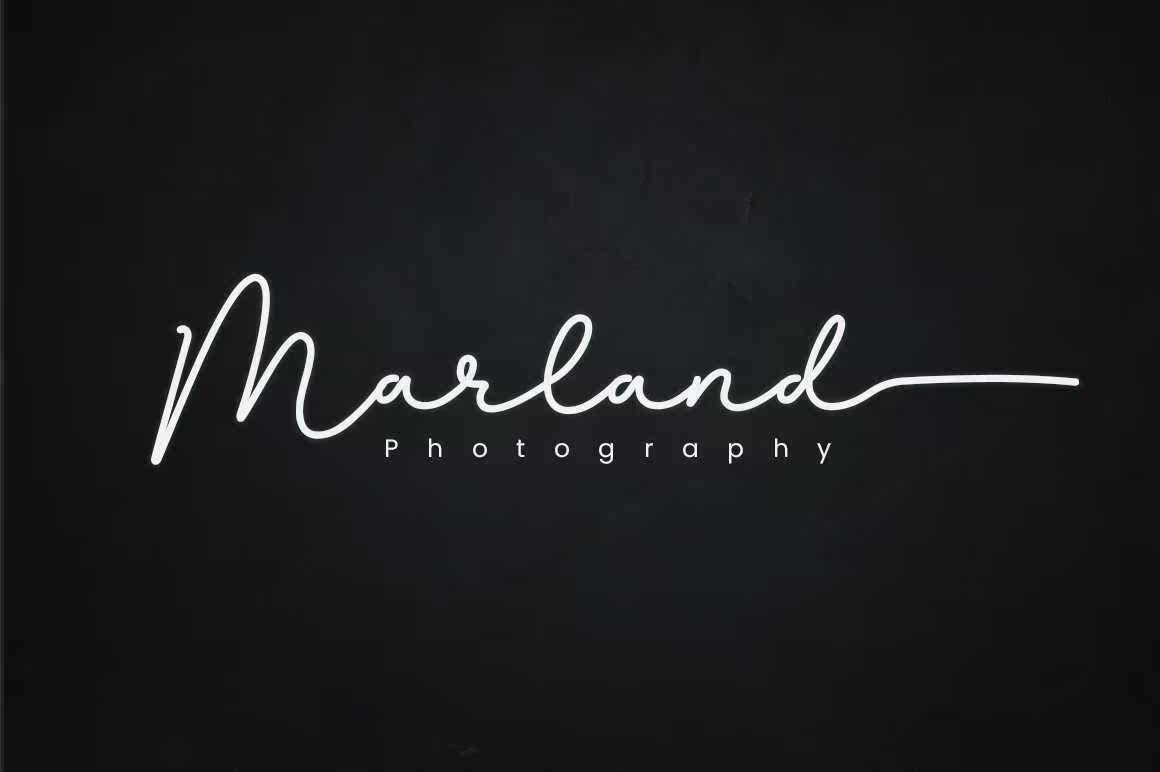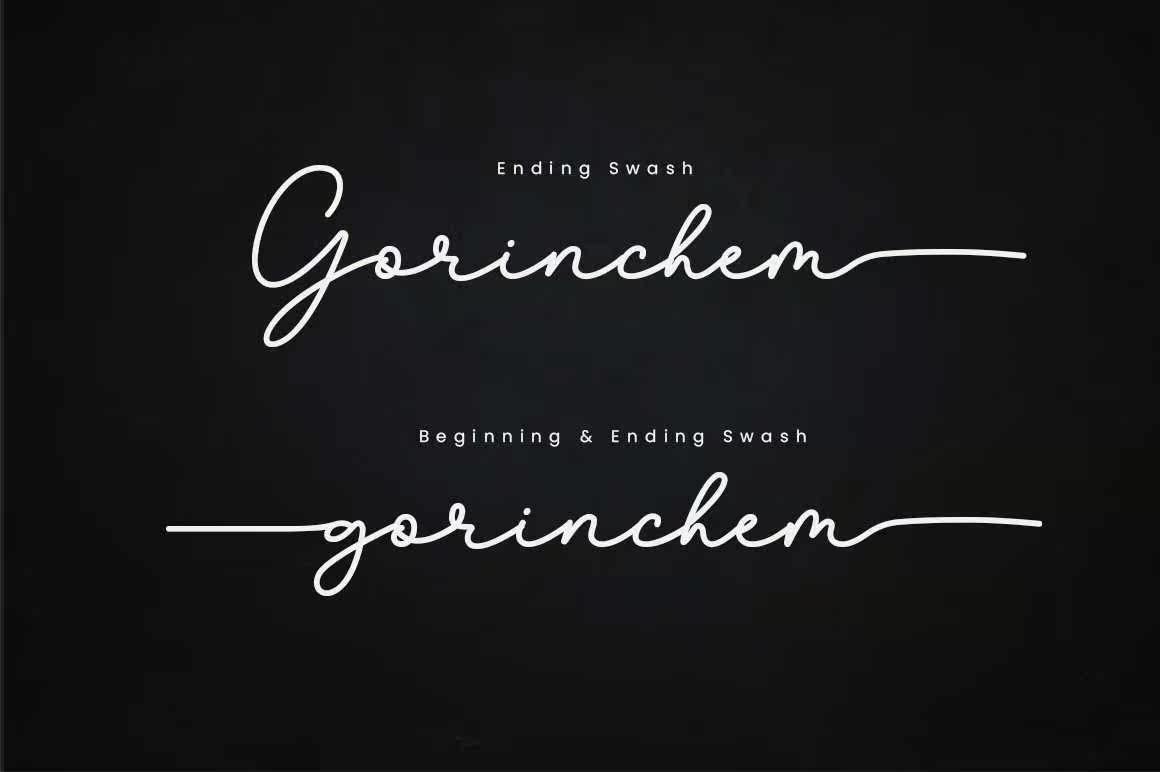
GorinChemisah和WrittenFontCreatedinMonolineStyles。这个Fonts有一个很好的风格,但它更没有优雅的风格,因为这个Fonts的特点是小写,因为这个Fonts的风格看似简单,但看起来很漂亮,很酷,还有许多其他的。Gorinchemisaha和WrittenFont都是以单线风格创建的。这个Font有一个很好的风格,但它更像是一个没有优雅风格的字体,因为这个Font的特点是小写的,因为它的风格很简单,但是看起来很漂亮,很酷,还有很多其他的字体。